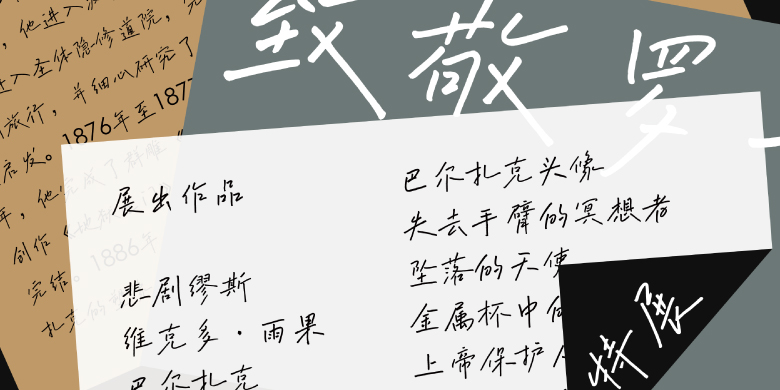
方正字迹-漫趣手写体
字体品牌: 方正字迹设计师:周佳敏 字体分类:创意书写 字体属性:精品字 字符集:大陆简体(GB2312-80) 发布时间: 2023
这是一款轻松趣味、随性自然的创意手写字体,其字形结构舒展,笔画设计简单亲和,多字组合富有手写节奏感,适合应用在广告、杂志、包装、绘本、游戏、影视综艺等追求洒脱、松弛的氛围当中。